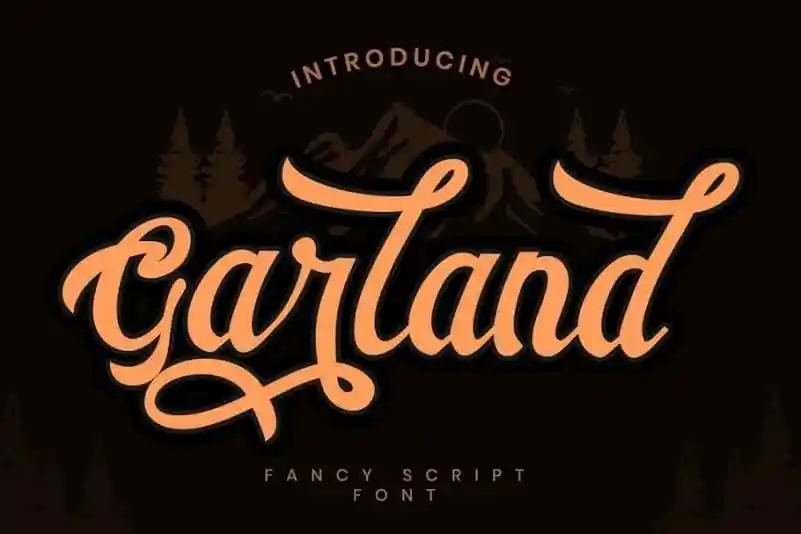
A Garland Script Font é uma elegante tipografia feita a mão, com linhas suaves e fluidas que capturam a essência do desenho à mão. Foi criada pelo estúdio de design PutraCetol Studio para o mundo moderno das letras cursivas inspiradas nos estilos de letra coloridas encontradas nas ruas da cidade. Esta fonte é uma amostra perfeita para quem busca um toque artístico e sofisticado em projetos digitais, seja para criar identidades visuais ou design gráfico, oferecendo sempre uma opção de flexibilidade no uso do texto. Ideal tanto para nomes de marca quanto para o design de interfaces de usuário, a Garland Script Font se destaca como um recurso indispensável na sua coleção de fontes.